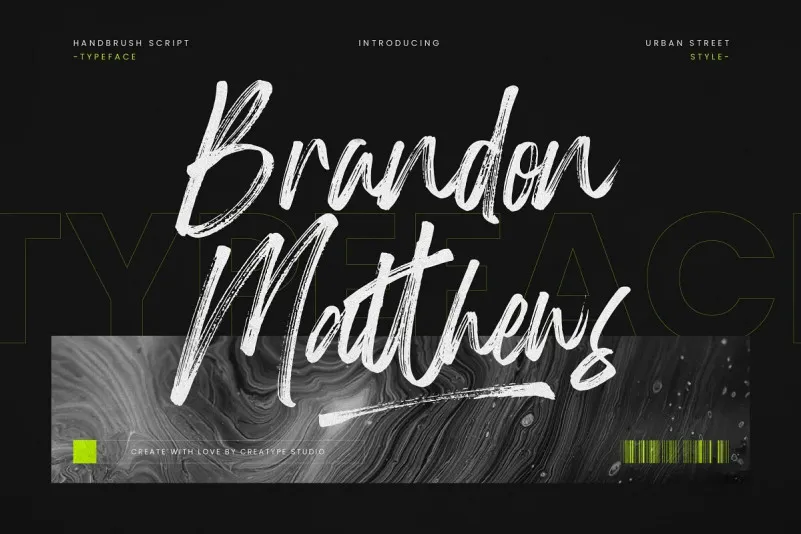
Brandon Matthews Font – Fonte Grátis
Brandon Matthews Font
Esta fonte ‘Brandon Matthews Font’ foi criada por Creatype Studio com um efeito de tira-dentes que oferece um estilo autêntico. Trata-se de uma tipografia desenhada à mão, perfeitamente adaptada para projetos de marca, logos, designs de casamento, posts nas redes sociais, anúncios, embalagens de produtos, design de produtos, etiquetas, fotografia, marcas d’água, convites e papelaria. Ideal para qualquer projeto que necessite do toque único da escrita a mão. Com o uso desta fonte, você pode adicionar um charme autêntico aos seus trabalhos gráficos. Esta font é uma opção perfeita para aqueles designers interessados em incorporar personalidade e realismo em suas criações digitais.